秀英体のコネタ
第15回 便利でかわいい見本帳『活版の栞/しおり』のこと
「書体見本帳」とは、書体の製造メーカーがお客様に対し、「この書体はこういうデザインですよ、これぐらい漢字が使えますよ」とアピールするための冊子です。明治はじめの「活字の父」本木昌造の崎陽新塾製造活字目録から、現在販売されているデジタルフォントまで、どのメーカーも作っています。
もちろん秀英体にもさまざまな活字見本帳があります。しかし今回のコネタでご紹介するのは、秀英舎/大日本印刷の活字見本帳のなかでも、ちょっと特別な見本帳「活版の栞/しおり」です。
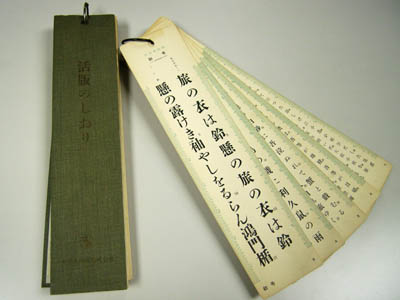
左が昭和36年版「活版のしおり」、右が昭和37年版「活版の栞」です。
昭和27年版と昭和36年版の違い
この見本帳は昭和27年に作成され、昭和36年に改訂されています。昭和27年版のタイトルが「活版の栞」で、昭和36年版が「活版のしおり」とひらがなに変更されています。
もちろん内容にも変化があります。昭和27年から36年までのあいだに、創業当時からの活字のサイズ体系であった号数制が社内で廃止され、ポイント制に完全移行しました。そのため、昭和27年版では号数とポイントのそれぞれが記載されていますが、昭和36年版はポイントのみです。
しかし号数からポイントに移植された書体もあります。たとえば昭和27年版に掲載されている初号は40ポイントに移植されました。本来は初号のほうが若干大きいのですが、秀英体の初号は活字の正方形のボディに対し小さめに作られていたため、うまく40ポイントに移植することができたようです。比べると文字のデザインはまったく一緒です。
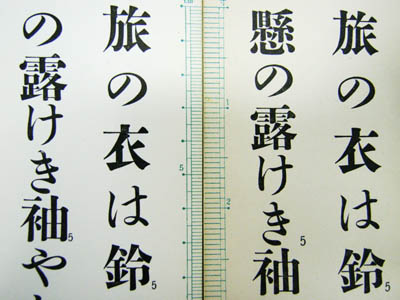
左が40ポイント明朝、右が初号明朝。
ここが便利(1) センチ&ポイントスケール
この見本帳には様々な便利機能が付与されています。まずは全ページの左右につけられた定規! センチとポイントが両方わかるので、急なサイズ計測にも安心です。(昭和27年版では尺とセンチでした)
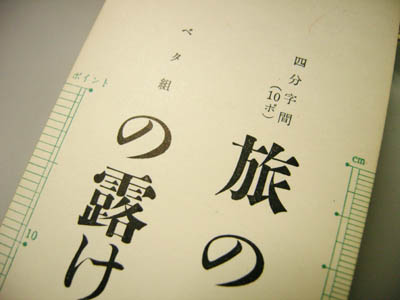
左にポイント、右にセンチ。
ここが便利(2) テキストが豊富
書体見本帳の多くは、決まった例文を書体を変えて見せています。しかしこの見本帳では、各書体でさまざまなテキストを使用し、実際に秀英体を使用した時の雰囲気を掴みやすく作られています。
例えば勧進帳の「旅の衣は鈴懸の~」、北原白秋『城ヶ島の雨』、早稲田・慶應・明治・法政・立教の各大学校歌、夏目漱石・島崎藤村・樋口一葉らの名著からの一文も。
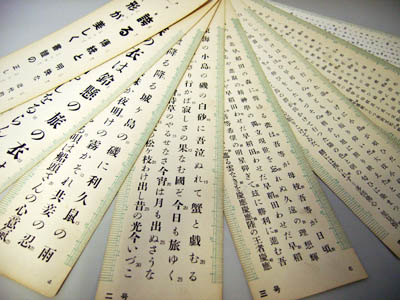
誰が選んでいたのかはわかりません。
ここが便利(3) 字間アキシミュレーション
字間のアキ量を変えて例文が印刷されているため、実際に書体を組版したときのイメージが湧きやすいです。例えば10ポイント明朝のページでは、アキの大きさを全角(10ポイント)・8ポイント・6ポイント・二分(5ポイント)・四分(2.5ポイント)・ベタ組みの6パターンを一覧できます。
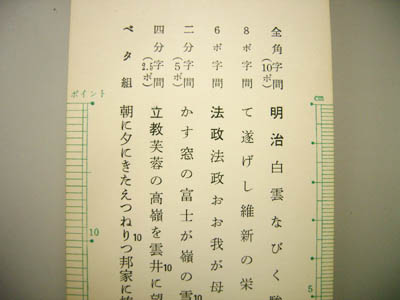
校歌を印刷するなら文字間がアキ気味のほうがかっこいいですね
ここが便利(4) 本文組版シミュレーション
本文サイズの書体ではさらに詳細に、文字サイズ・段数・行間・ルビ・判型・縦横組を確認することが可能です。ルビはパラルビと総ルビをひとつのページで比べられるように作ってあります。欧文のページも用意されています。
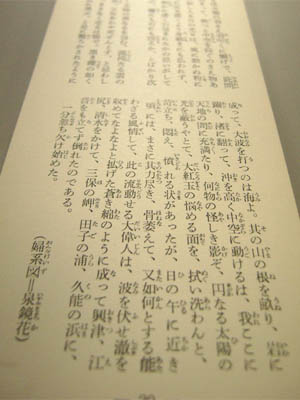
泉鏡花『婦系図』で具体的な組版イメージがつかめます。
ここが便利(5) 印刷豆知識
巻末には、印刷の豆知識がまとまっています。校正記号表・面付時のページの並び方・規格サイズの仕上がり寸法など、知っていると便利な内容が厳選されています。
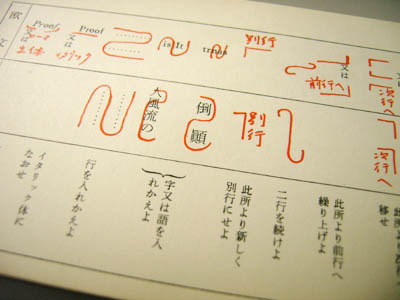
欧文と和文それぞれの校正記号がわかるようになっています。
ここが便利(6) 細長くてリング綴じ
既にお気づきかと思いますが、普通の冊子の形ではありません。縦30.5×横7センチの細長い形をしており、さらに開閉可能な金属のリングで綴じられているので、各ページを一枚ずつばらして使うことも可能です。
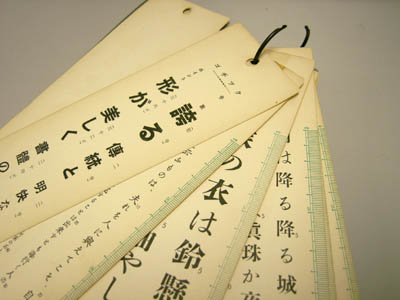
リングなので見たいページもばっちり見ることができます。
この見本帳、どうしてこんなに実用的なのでしょうか。
実は、DNPの営業が持ち歩く用に製作された見本帳だからなのです。いつも携行できるようにバッグに入る細さ、いざというときにさっと取り出し書体や組版の具体的なイメージが共有できる内容なのも納得です。
若い頃に営業を担当していたベテラン社員にこの見本帳を見せると、必ず「お~、なつかしい!」「俺も持ってたよ~」と声があがります。誰もがバリバリ使っていたようです。そのせいか、この見本帳が社内では使い込んだボロボロの姿で見つかることが多いのですが、営業活動の汗と涙が染み込むほど常に持ち歩いてもらえたという証だと思います。